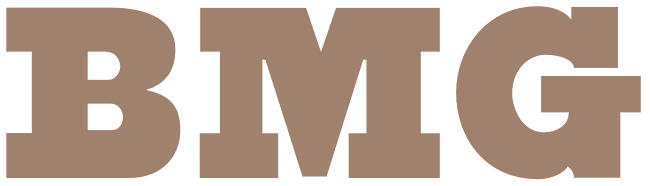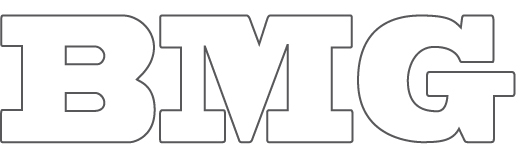
was könnte das für eine schrift sein
ich habe soeben eine visitenkarte mit altem logo eines kunden bekommen und es soll zum einen nachgebaut und / oder überarbeitet werden - ich habe aber nur leider nicht den gerinsten dunst was für eine schrift das ist da es anscheinenend ein extra fetter schnitt ist.
hat jemand eine idee?
Austin Antique kommt ganz gut hin, wobei das B wahrscheinlich noch gezerrt wurde.
Blackoak, auf 50 % Breite gequetscht. Das ergibt dann das kaputte G :-)